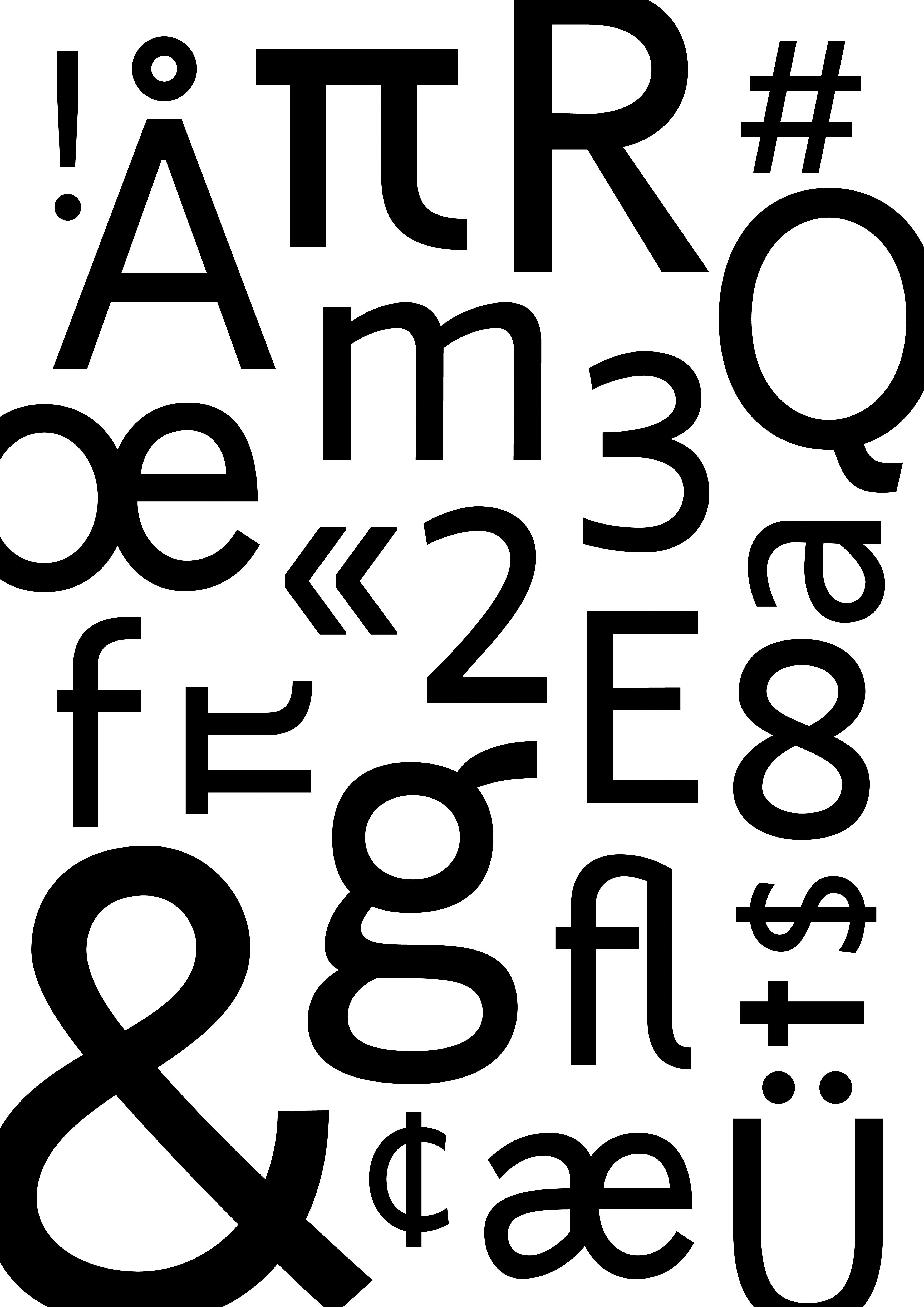
Didactica
| Descripción | La tipografía didáctica es una fuente gratuita creada para facilitar la elección tipográfica a la hora de crear materiales didácticos para enseñar a leer a los niños, basada en la investigación de la legibilidad y la lecturabilidad, y desde una perspectiva caligráfica. La fuente está enfocada en las primeras lecturas infantiles (y soporta el alfabeto latino). |